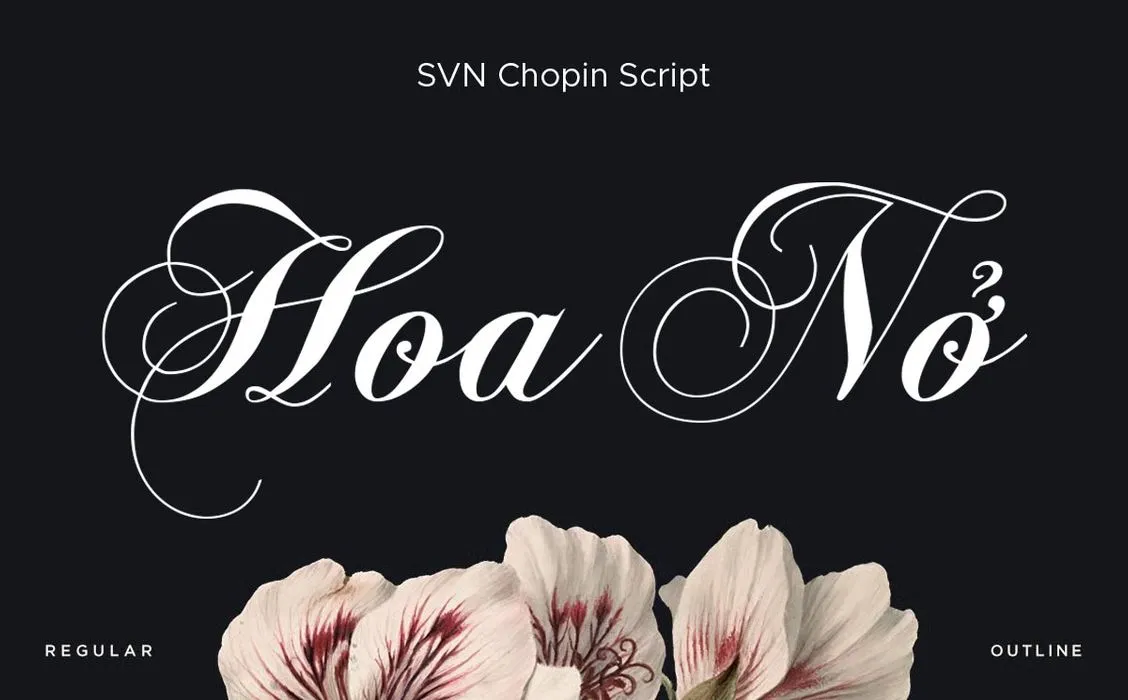
Phông chữ miễn phí viết tay SVN Chopin Script Việt hóa là một trong những bộ font chữ nghệ thuật (calligraphy script) vô cùng nổi tiếng, mang đậm phong cách tân cổ điển đầy lãng mạn và quý phái. Bộ font này được việt hóa tỉ mỉ bởi SVN, giúp giữ nguyên vẹn đường nét uốn lượn mềm mại nguyên bản mà vẫn tương thích hoàn hảo với hệ thống dấu tiếng Việt. Nếu bạn đang tìm kiếm một kiểu chữ để tôn lên vẻ đẹp thanh lịch cho các dự án thiết kế thiệp cưới, nhận diện thương hiệu hay ấn phẩm truyền thông, SVN Chopin Script Việt hóa chính là sự lựa chọn hoàn hảo không thể bỏ qua.
Khám Phá Phông Chữ Miễn Phí Viết Tay SVN Chopin Script Việt Hóa – Giải Pháp Typography Sang Trọng Và Tinh Tế
Nghệ thuật Typography trong thiết kế đồ họa hiện đại đòi hỏi sự kết hợp hài hòa giữa tính thẩm mỹ và khả năng truyền tải thông điệp. Trong số hàng nghìn bộ font chữ script hiện nay, font SVN Chopin Script Việt hóa luôn chiếm một vị trí đặc biệt trong lòng cộng đồng nhà thiết kế tại Việt Nam. Được phát triển dựa trên nền tảng của phông chữ Polonaise kinh điển, Chopin Script mang trong mình hơi thở lãng mạn của âm nhạc cổ điển, đúng như tên gọi được lấy cảm hứng từ nhà soạn nhạc thiên tài Frédéric Chopin.
Phiên bản việt hóa SVN Chopin Script đã giải quyết triệt để bài toán thiếu hụt ký tự dấu tiếng Việt – một trong những hạn chế lớn nhất của các phông chữ viết tay nước ngoài. Các dấu thanh, dấu mũ được thiết kế trau chuốt, tỉ mỉ sao cho không phá vỡ cấu trúc tổng thể của từ, đồng thời giữ được độ cân bằng hoàn hảo giữa các con chữ. Điều này giúp các nhà thiết kế tự do sáng tạo mà không lo lắng về lỗi hiển thị hay mất thẩm mỹ khi gõ tiếng Việt trong các sản phẩm thương mại cũng như cá nhân.
1. Hỗ Trợ Đầy Đủ Bộ Ký Tự Tiếng Việt Chuẩn Unicode Tối Ưu
Một trong những ưu điểm vượt trội nhất của phông chữ miễn phí viết tay SVN Chopin Script Việt hóa chính là việc tích hợp trọn bộ ký tự tiếng Việt theo chuẩn Unicode. Quá trình việt hóa không chỉ đơn thuần là ghép các dấu thanh vào chữ cái có sẵn, mà là một sự tinh chỉnh nghệ thuật công phu. Đội ngũ việt hóa đã tính toán kỹ lưỡng về góc độ, khoảng cách (kerning) và độ dày của từng dấu câu như dấu sắc, huyền, hỏi, ngã, nặng, các dấu mũ (â, ê, ô) và dấu móc (ư, ơ).
Nhờ đó, khi bạn nhập liệu bằng các bộ gõ phổ biến như UniKey hay VietKey ở bảng mã Unicode chuẩn, phông chữ sẽ hiển thị mượt mà, không gặp hiện tượng lỗi font, mất dấu hay lệch vị trí ký tự. Điều này giúp tiết kiệm thời gian đáng kể cho các designer trong quá trình tinh chỉnh thủ công, đồng thời đảm bảo ấn phẩm in ấn hoặc xuất bản số đạt chất lượng thẩm mỹ cao nhất.
2. Đường Nét Script Bay Bổng, Sang Trọng Và Mang Đậm Tính Nghệ Thuật
SVN Chopin Script Việt hóa sở hữu kiểu dáng uốn lượn đặc trưng của phong cách Calligraphy (chữ viết tay nghệ thuật truyền thống). Điểm đặc biệt của font chữ này nằm ở sự tương phản rõ rệt giữa các nét thanh mỏng manh và các nét đậm mạnh mẽ. Sự biến thiên độ dày của nét chữ tạo nên hiệu ứng thị giác sinh động, tựa như những đường nét được viết ra từ chiếc bút lông hay bút mực máy cao cấp của các nghệ nhân thư pháp Tây Phương.
Các chữ cái in hoa (Uppercase) trong SVN Chopin Script được tạo hình vô cùng bay bổng với những đường xoắn nghệ thuật, tạo điểm nhấn ấn tượng cho phần mở đầu của các tiêu đề. Trong khi đó, các chữ cái in thường (Lowercase) lại nối tiếp nhau một cách tự nhiên, tạo cảm giác liền mạch và nhịp nhàng. Sự cân bằng này giúp font chữ vừa giữ được nét quyến rũ cổ điển, vừa mang tính ứng dụng cao mà không gây rối mắt cho người xem.
3. Lựa Chọn Hàng Đầu Cho Thiết Kế Thiệp Cưới Và Sự Kiện Sang Trọng
Thiệp cưới, thiệp mời sự kiện cao cấp hay thư cảm ơn luôn yêu cầu những kiểu chữ thể hiện được tính trang trọng, tinh tế và đầy cảm xúc. Phông chữ miễn phí viết tay SVN Chopin Script Việt hóa chính là sự lựa chọn ưu tiên trong phân khúc thiết kế này. Sự mềm mại, uyển chuyển của phông chữ giúp truyền tải thông điệp tình yêu và sự trân trọng một cách trọn vẹn nhất.
Khi được ứng dụng trên các chất liệu giấy mỹ thuật, giấy ánh kim, hoặc kết hợp với các kỹ thuật in ấn cao cấp như ép kim (foiling), dập nổi (embossing), SVN Chopin Script Việt hóa càng làm nổi bật vẻ sang trọng quý phái. Tên chú rể – cô dâu hay tên khách mời khi gõ bằng font chữ này đều trở thành một tác phẩm nghệ thuật thu nhỏ, ghi lại dấu ấn khó quên trong lòng người nhận.
4. Tối Ưu Cho Truyền Thông Mạng Xã Hội, Trích Dẫn Và Thiết Kế Bao Bì
Không chỉ dừng lại ở các ấn phẩm in ấn truyền thống, font chữ viết tay SVN Chopin Script Việt hóa còn thể hiện sức mạnh vượt trội trong mảng thiết kế nội dung số. Trào lưu tạo các bức ảnh chứa trích dẫn (quote), thơ ca hay thông điệp truyền cảm hứng trên các nền tảng như Instagram, Facebook, Pinterest đang ngày càng phát triển. Sự xuất hiện của SVN Chopin Script giúp các bức ảnh trở nên thơ mộng, có chiều sâu và thu hút sự tương tác của người xem.
Bên cạnh đó, trong lĩnh vực thiết kế bao bì sản phẩm – đặc biệt là các ngành hàng như mỹ phẩm thiên nhiên, nến thơm, nước hoa, trà thảo mộc hay thời trang vintage – kiểu chữ script này tạo nên vẻ ngoài thân thiện, thủ công (handcrafted) và đẳng cấp. Nó giúp thương hiệu truyền tải thông điệp về sự tỉ mỉ, tinh tế trong từng sản phẩm đến tay khách hàng.